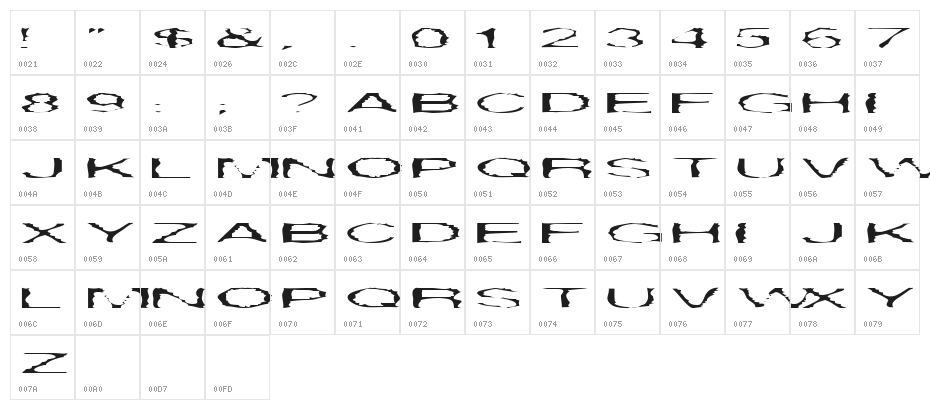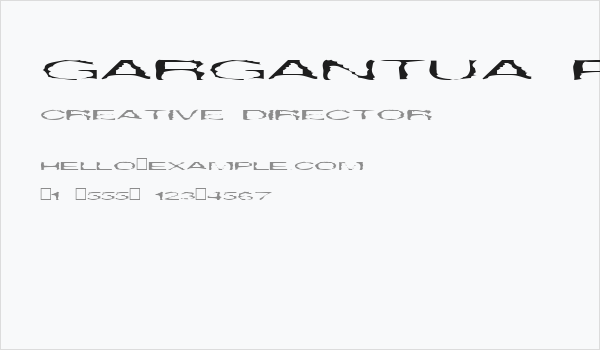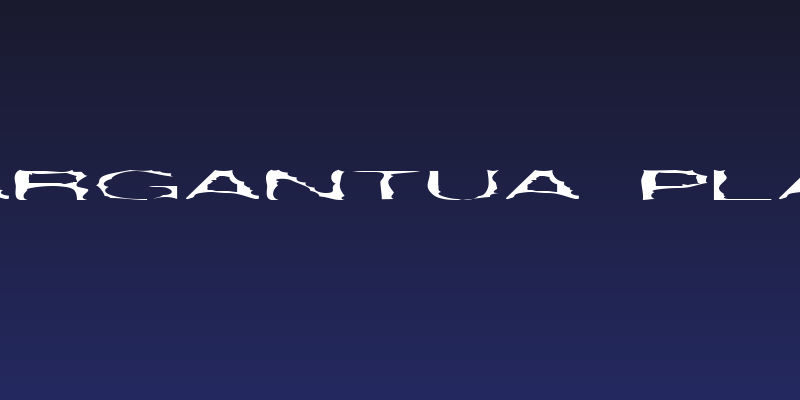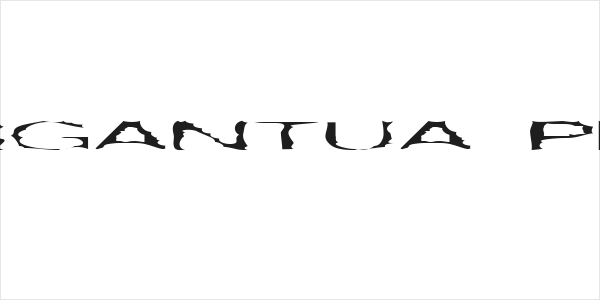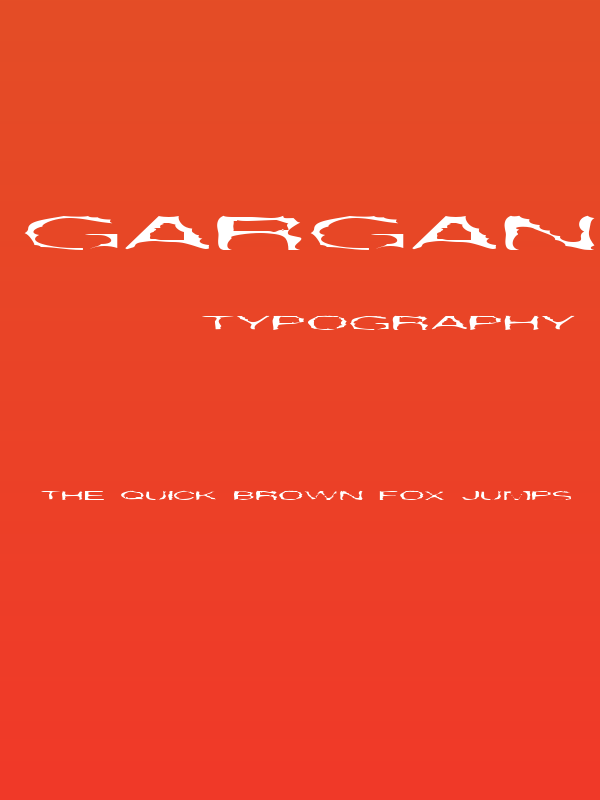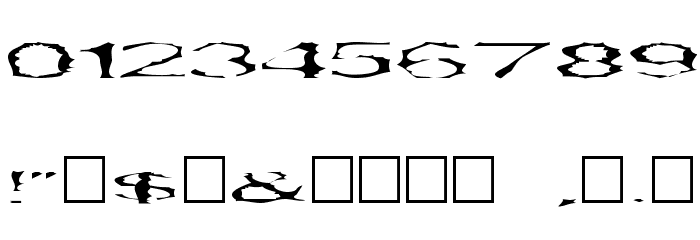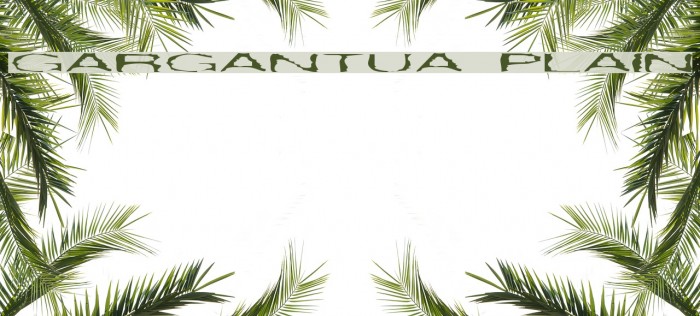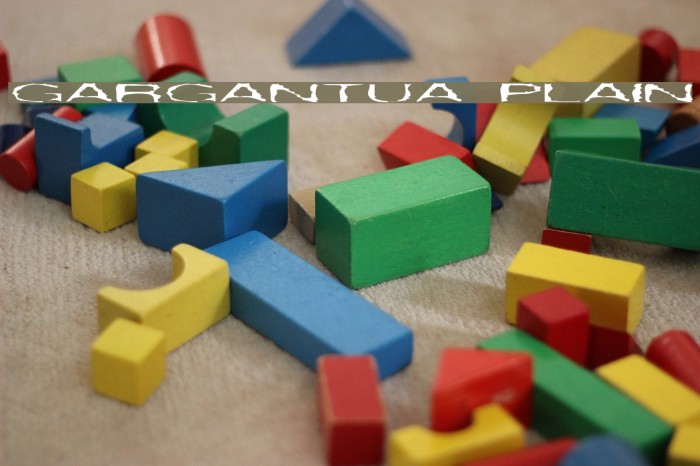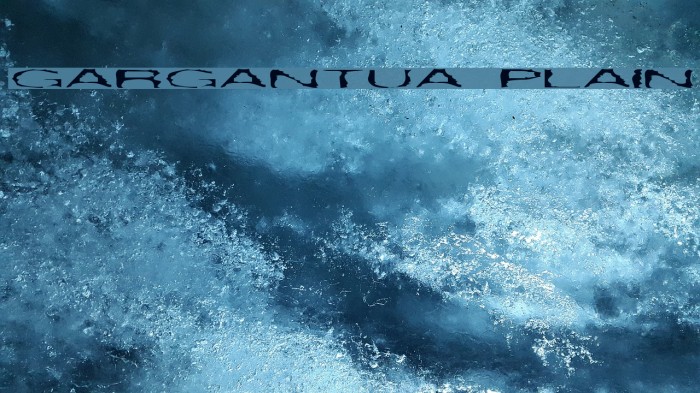
Gargantua Plain Font
Fonts by Marty Bee - www.martybee.com
Questo font include 75 caratteri. Clicca su un carattere per vedere i dettagli.
| Progetti proposti | Ideal for album covers, posters, branding for edgy or alternative products, and any design needing a bold, artistic touch. |